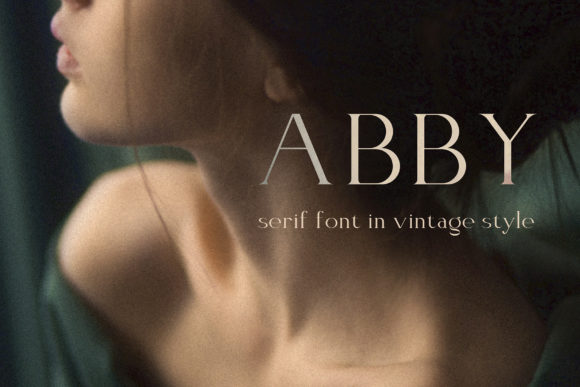
Elegant Font Abby
Если вы ищете высококачественные ресурсы, такие как Elegant Font Abby, этот премиум-пакет — фантастический выбор для ваших творческих проектов.
Создаете ли вы продукты POD (печать по требованию), свадебные приглашения или графику для социальных сетей, Elegant Font Abby станет идеальным выбором.